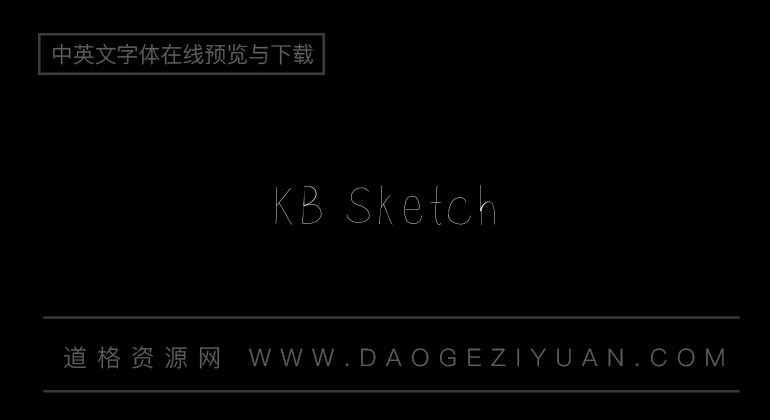
KB Sketch
KB Sketch 是一款非常有趣的手写字体,具有手绘风格的特点。它的字母形状不是固定不变的,而是像是由手绘画笔一笔一笔地描绘出来的,带有一定的颤动和自然的不规则性,使得文字看起来更加生动、活泼。这种风格适合用于各种儿童、卡通、漫画等类型的设计作品,能够带给人们一种童真、愉悦、温馨的感觉。
KB Sketch是一款非常不错的手写艺术字体,具有很好的视觉感,适合于文化类的宣传设计、商业类品牌的广告和产品包装设计以及个性化文字排版等较多场景。